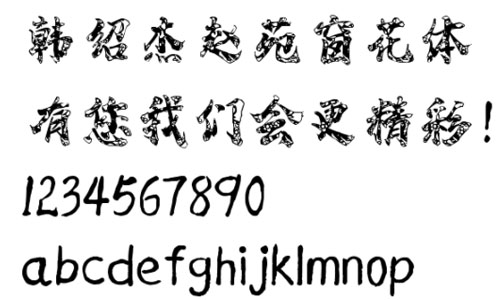
韓紹杰趙苑窗花體字體是一款帶有窗花圖形設計的中文藝術(shù)字體,每款中文字體的筆畫上都有窗花圖案,非常有意思,能夠應用于文本裝潢、信息展示、網(wǎng)頁設計、篆刻制模、數(shù)據(jù)制作、裝潢設計、計算藝術(shù)設計、視覺設計、字帖等一切合法應用場景,歡迎需要的朋友前來下載使用。